明朝体
明朝体(みんちょうたい)は印刷で用いられる書体の一つ。特徴として縦線が太く横線が細くなっていて、横線の右端と曲り角の右肩に三角形の山(ウロコ)があります。中国の明代の書籍で用いられた書体が発祥とされています。また、欧文フォントのセリフ体に似ています。
明朝体一覧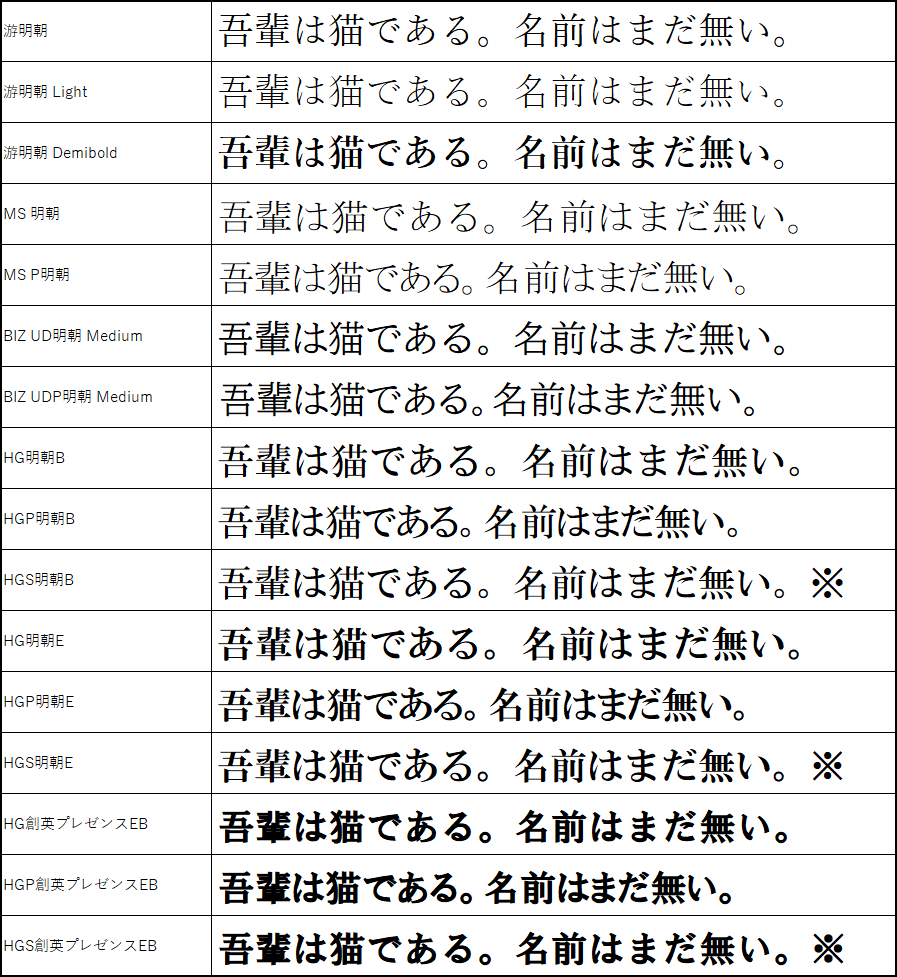
※=半角文字だけプロポーショナルフォント。
游書体
游書体は等幅フォントとプロポーショナルフォントの両方の特性を合わせもったフォント。「 Light」「Demibold」は太さの違いを表す。
游明朝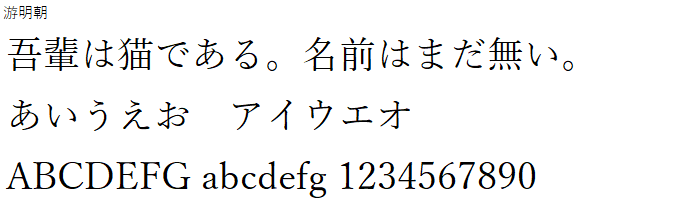
游明朝 Light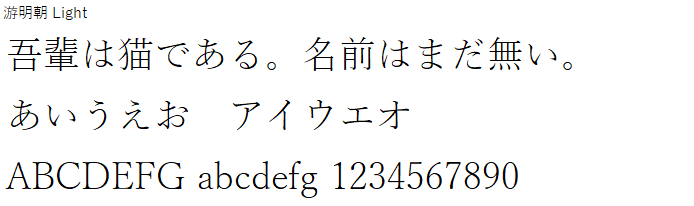
游明朝 Demibold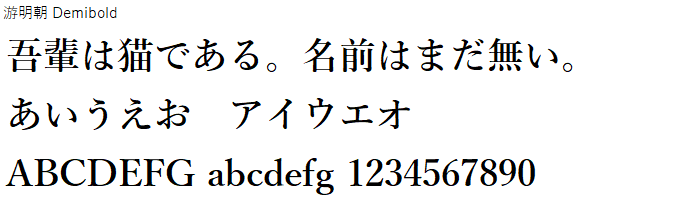
MS書体
游書体が登場するまではオフィスソフトの標準フォントだった。
MS 明朝(等幅フォント)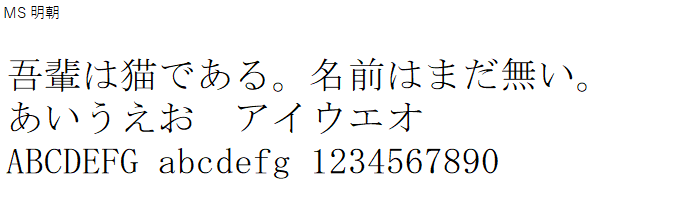
MS P明朝(プロポーショナルフォント)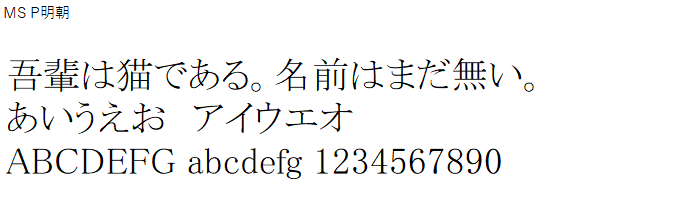
ユニバーサルデザイン書体
ユニバーサルデザイン書体は、可読性・視認性・判読性が高くなるようにデザインされたフォント。UDと略す。
BIZ UD明朝 Medium(等幅フォント)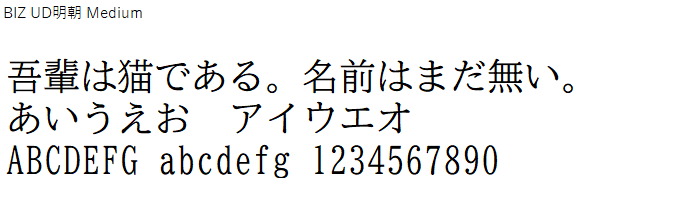
BIZ UDP明朝 Medium(プロポーショナルフォント)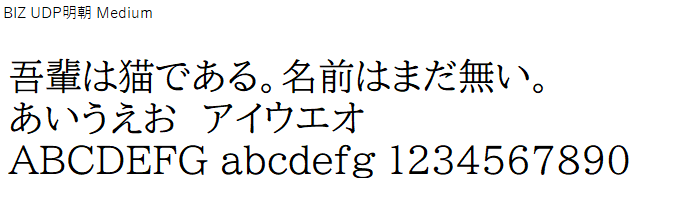
HG書体
HGは「High Grade」の略で、B・E・EBは文字の太さを表す。
HG明朝B(等幅フォント)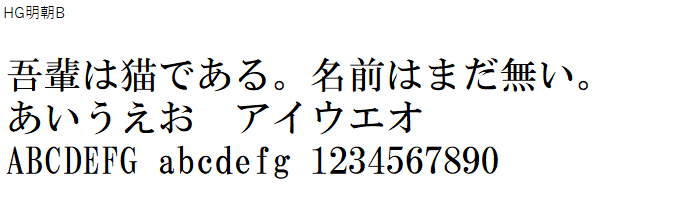
HGP明朝B(プロポーショナルフォント)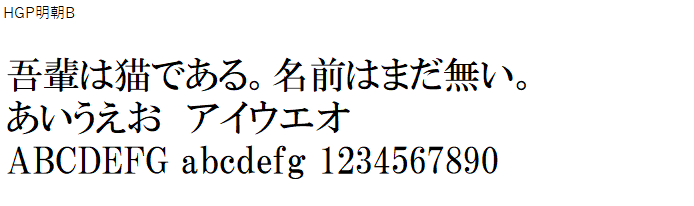
HGS明朝B※半角文字だけプロポーショナルフォント。
HG明朝E(等幅フォント)
HGP明朝E(プロポーショナルフォント)
HGS明朝E※半角文字だけプロポーショナルフォント。
HG創英プレゼンスEB(等幅フォント)
HGP創英プレゼンスEB(プロポーショナルフォント)
HGS創英プレゼンスEB※半角文字だけプロポーショナルフォント。